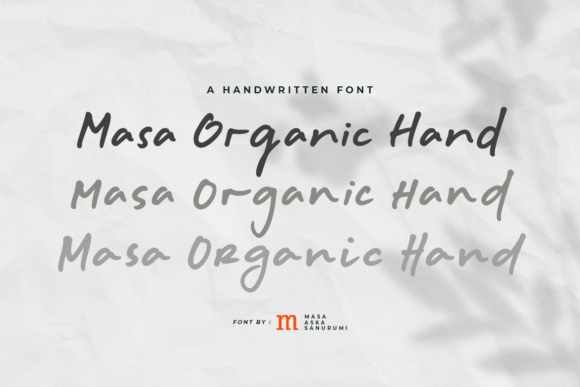
Masa Organic Hand
หากคุณกำลังมองหาเนื้อหาคุณภาพสูงเช่น Masa Organic Hand แพ็คเกจพรีเมียมนี้เป็นตัวเลือกที่ยอดเยี่ยมสำหรับโปรเจ็กต์สร้างสรรค์ของคุณ
สร้างขึ้นอย่างแม่นยำ Masa Organic Hand ให้เวกเตอร์ที่สะอาด พิมพ์ตัวอักษรที่ราบรื่น และใบอนุญาตเชิงพาณิชย์เพื่อความสบายใจ
ไม่ว่าคุณจะสร้างผลิตภัณฑ์ POD (Print on Demand) คำเชิญงานแต่งงาน หรือกราฟิกโซเชียลมีเดีย Masa Organic Hand ก็เหมาะสมอย่างยิ่ง